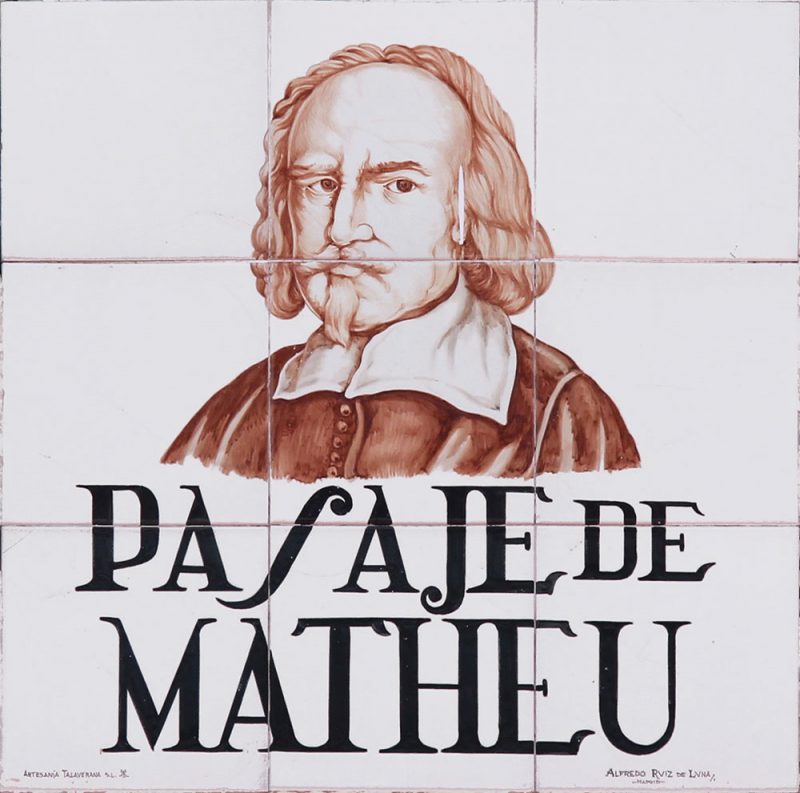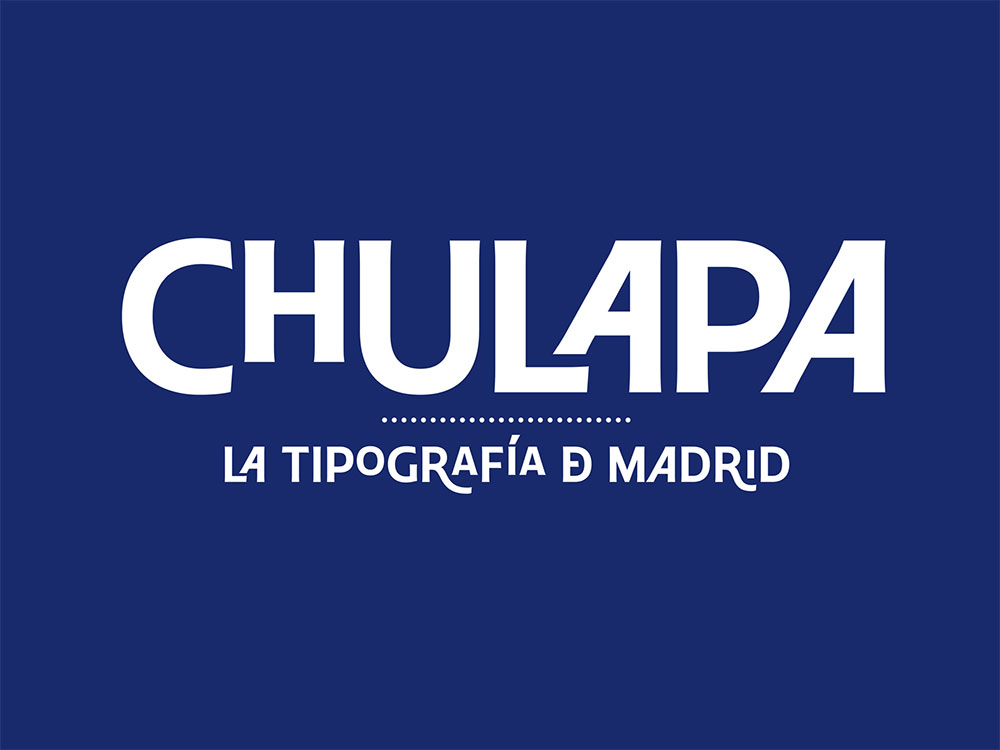
Tipografías y cerámica talaverana
Uno de los rasgos distintivos de Madrid son sin lugar a dudas las placas cerámicas que dan nombre a calles, plazas y lugares clave de su centro histórico. Estas piezas, creadas por el ceramista toledano Alfredo Ruiz de Luna para completar y complementar la señalética de la parte antigua de la capital española, han servido como punto de partida para el desarrollo de Chulapa, la primera tipografía de Madrid. Se trata de una serie de tipos de palo seco no geométrico con algunas características de la rotulación manual, producida por los diseñadores Joan Carles Casasín y Pablo Gámez.
Dotada de las variaciones suficientes para respetar la intención de la rotulación original, como tamaño, ubicación, ligaduras,… Chulapa ofrece la posibilidad de crear logotipos no necesariamente sistemáticos.
La fuente ha sido desarrollada y presentada en el marco de las fiestas de San Isidro y como era de esperarse, ha sido protagonista absoluta de la gráfica de este año. En 2018, un antecedente que es necesario mencionar, la diseñadora Silvia Fernández Palomar creo una tipografía similar, inspirada también en el trabajo de Ruiz de Luna y que fue utilizada en los ya celebres carteles de Mercedes DeBellard.